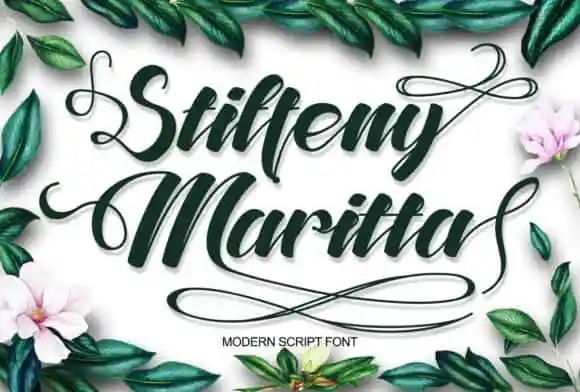
A Stiffeny Maritta é uma fonte de script elegante que combina sofisticação, elegância e modernidade num único design. Seu feitio suave e fluido torna-a perfeita para diversos projetos, desde logotipos e marca até convites, encomendas e designs para casamentos. Com sua leveza e estilo próprio, ela é perfeita para aqueles que buscam uma fonte de escrita manuscrita sofisticada para suas criações inovadoras. É a escolha ideal para quem deseja dar um toque especial a postagens do Instagram ou cartões de aniversário, fazendo-as se destacarem da multidão. Seu estilo distintivo e eterno certamente cativará qualquer designer que procura uma fonte elegante e versátil para seus trabalhos. Descubra por si mesmo os inúmeros usos possíveis desta maravilhosa fonte de script, e veja por que ela é a escolha perfeita para quem busca o respiro único e profundo da escrita manuscrita em cada projeto.